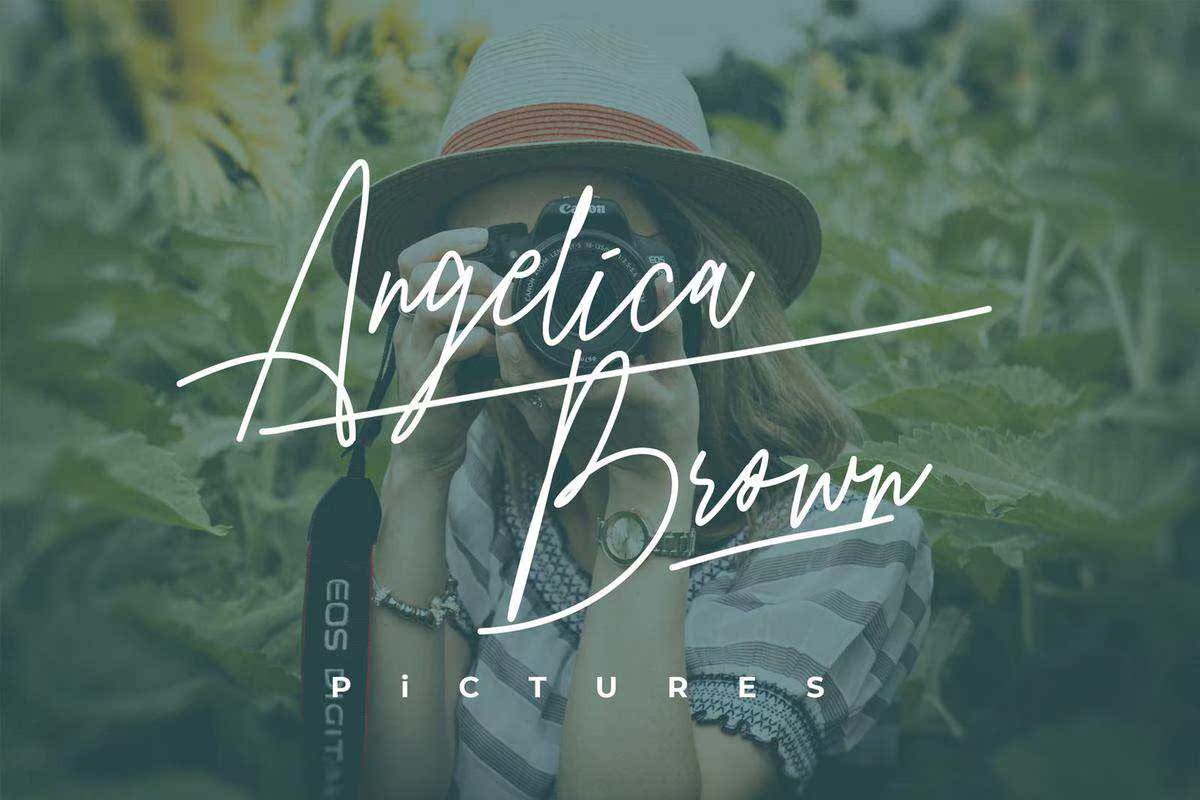
Pakotha的签名字体不带LegantLines。适用于您的品牌、产品、贺卡、婚礼或任何东西。Pakotha的内容包含基本的英语和其他多语言支持。可以安装Illustrator、Photoshop或Crosoftword等简单的应用程序。Pakotha已准备好帮助您进行美丽的设计!Pakotha的签名字体不带LegantLines。适用于您的品牌、产品、贺卡、婚礼或任何东西。Pakotha的内容包含基本的英语和其他多语言支持。可以安装Illustrator、Photoshop或Crosoftword等简单的应用程序。Pakotha已准备好帮助您进行美丽的设计!